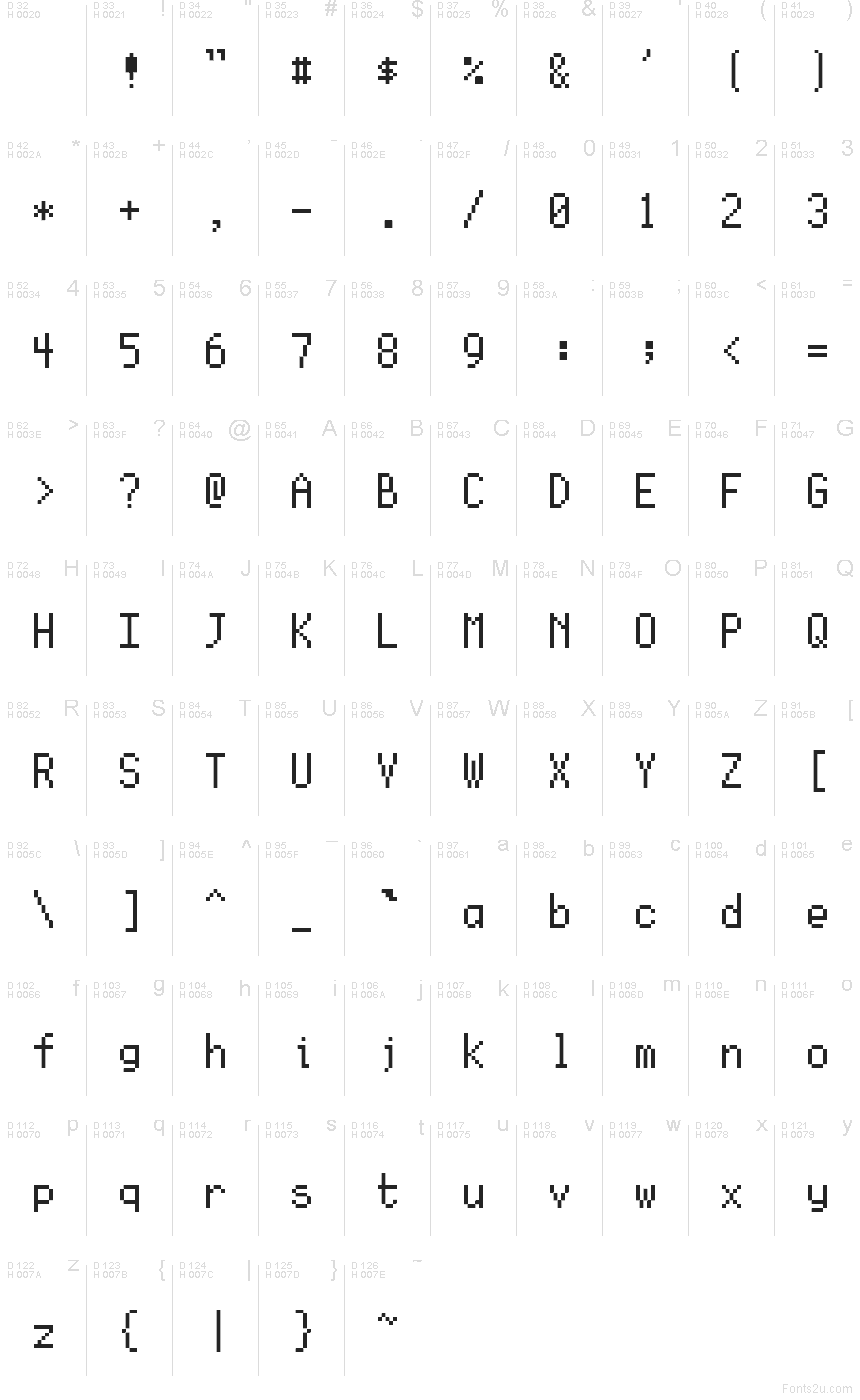
Wyvern od TLF je bezplatné pixelové písmo postavené z ostrých obdélníkových modulů a prudkých pravouhlých zlomů. Jeho nerovnoměrná šířka písmen, přerušené spoje a střídání vysokých a kompaktních tvarů dodávají písmu glitchový nádech raných počítačů.
Technologie a retro hraní jsou jeho nejjasnějším teritoriem. Dokáže vdechnout podobu plakátům pro herní automaty, herním menu i vizuálům elektronické hudby se vzhledem nízkorozlišovacího displeje dotaženého do nepravidelnějších tvarů. Tato sdílená digitální textura jej činí užitečným pro sci-fi akce, kde se písmena stávají součástí rozhraní namísto neutrálního textu.